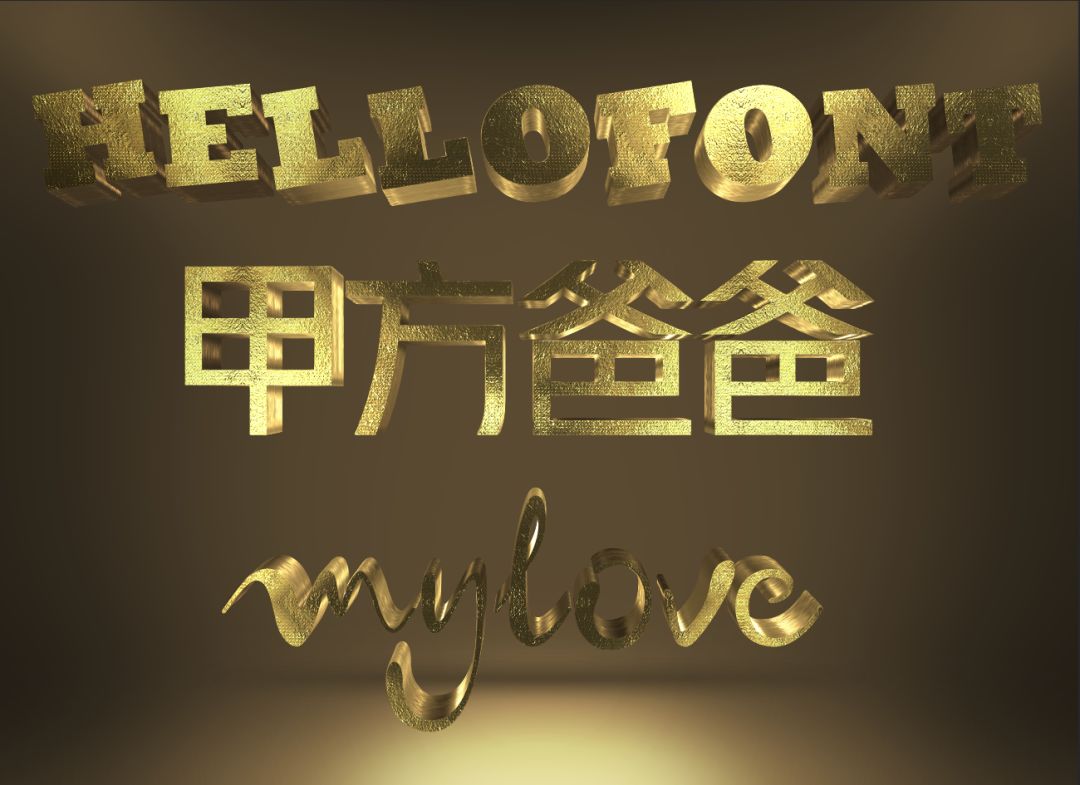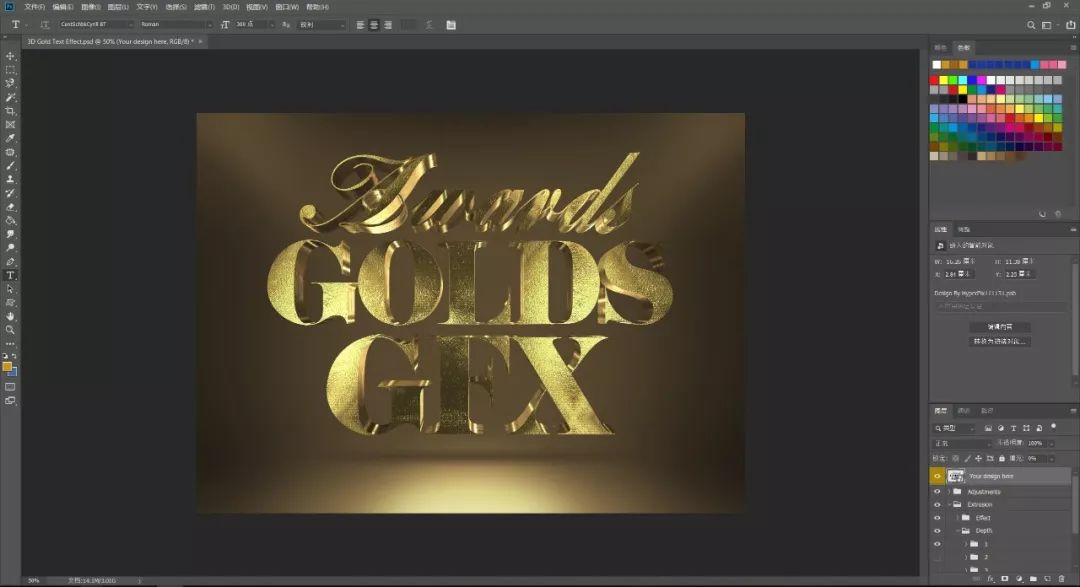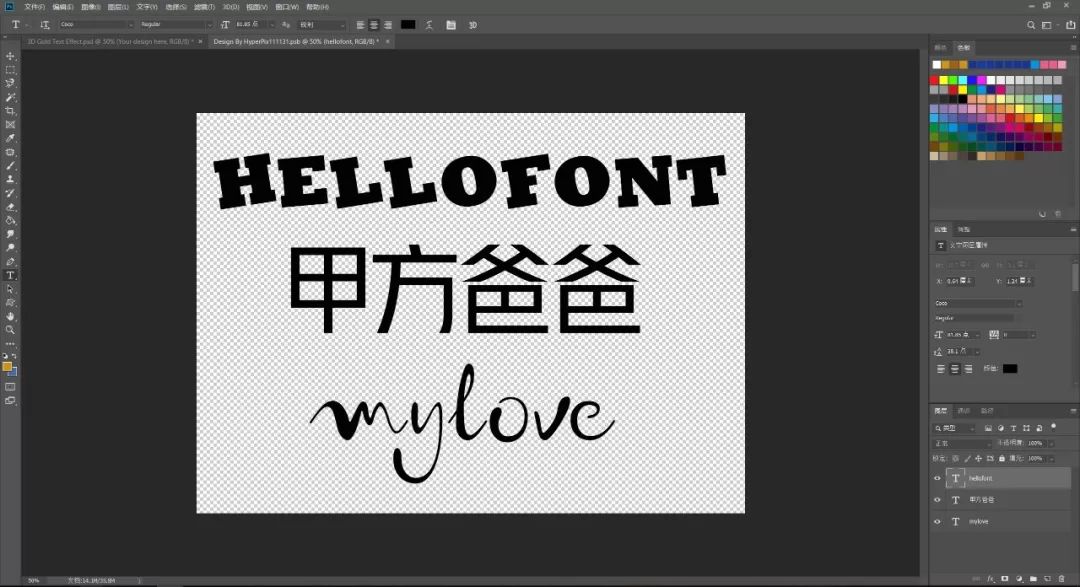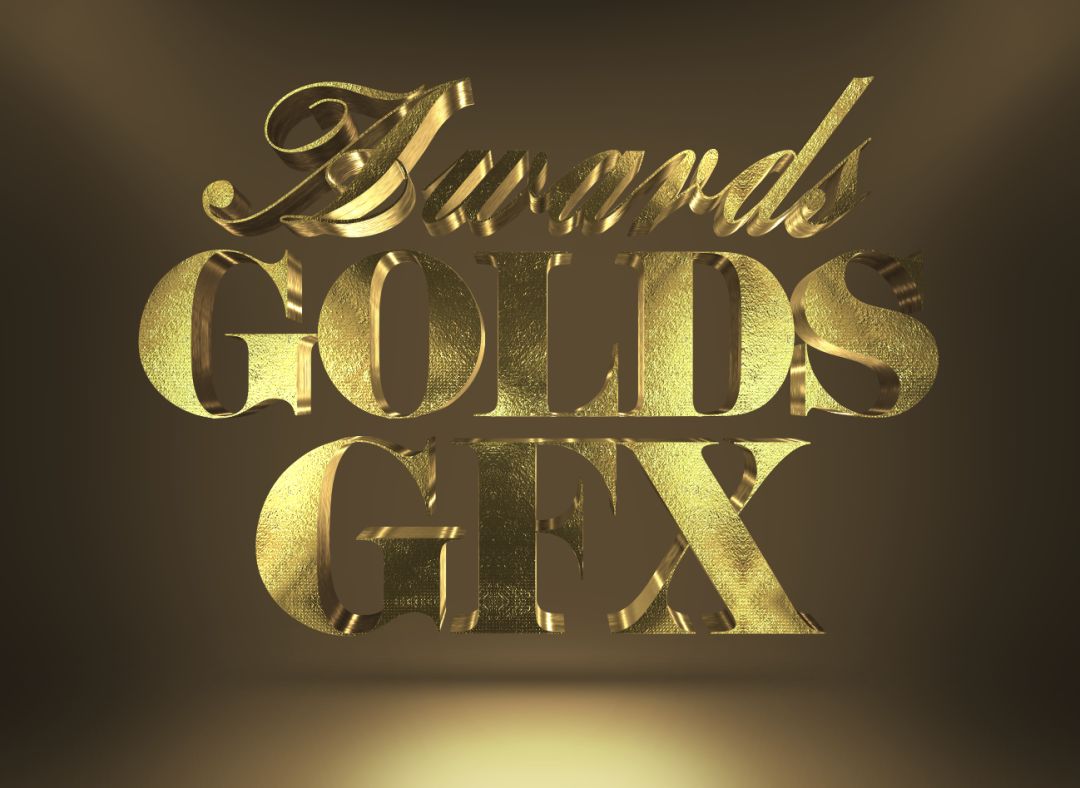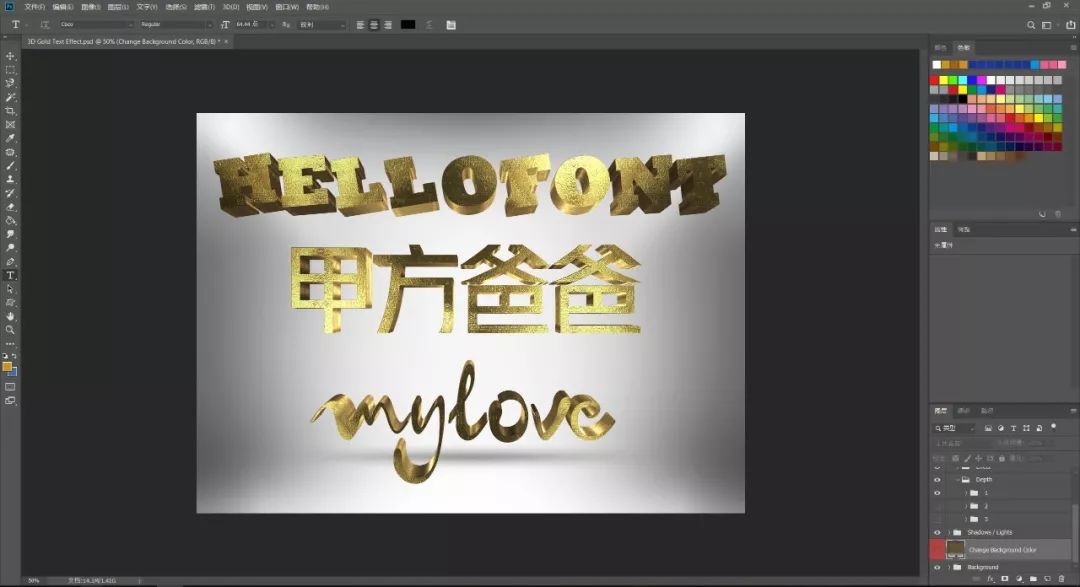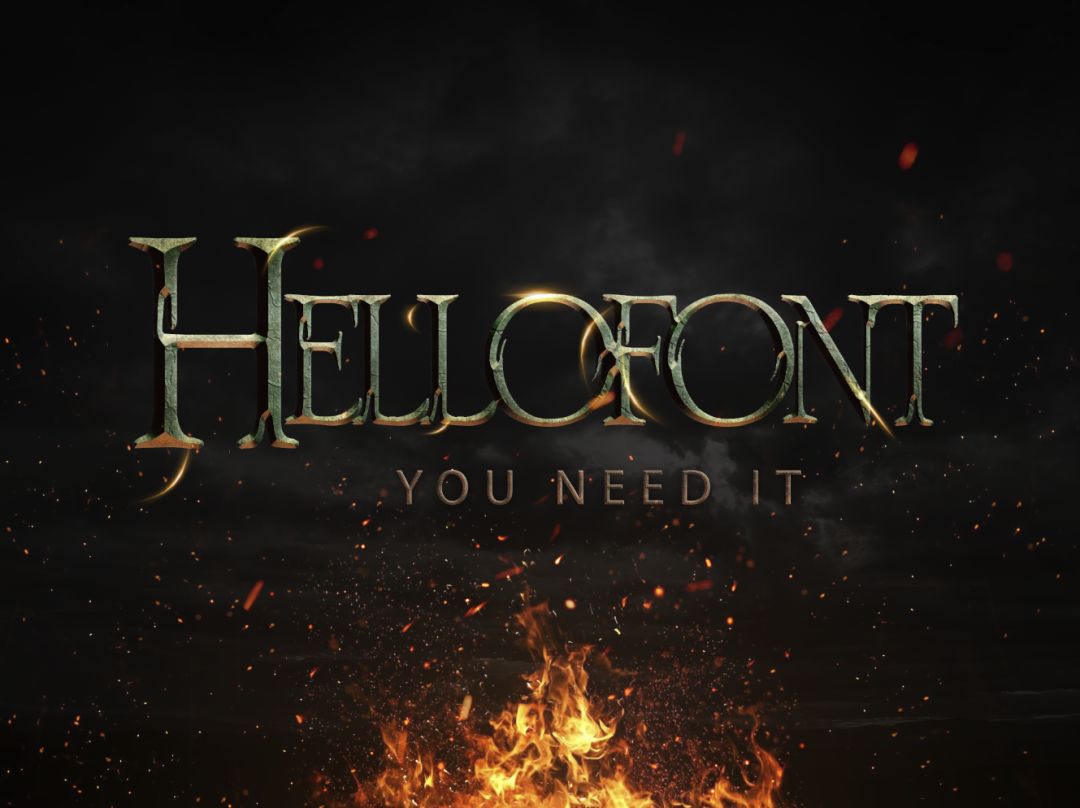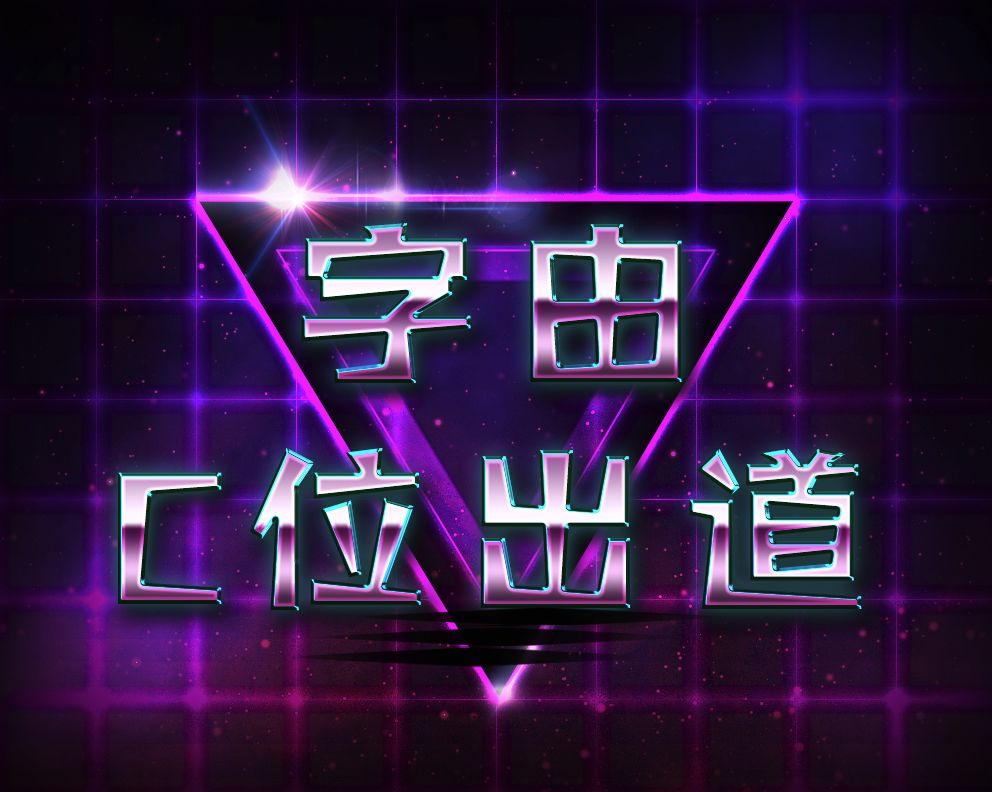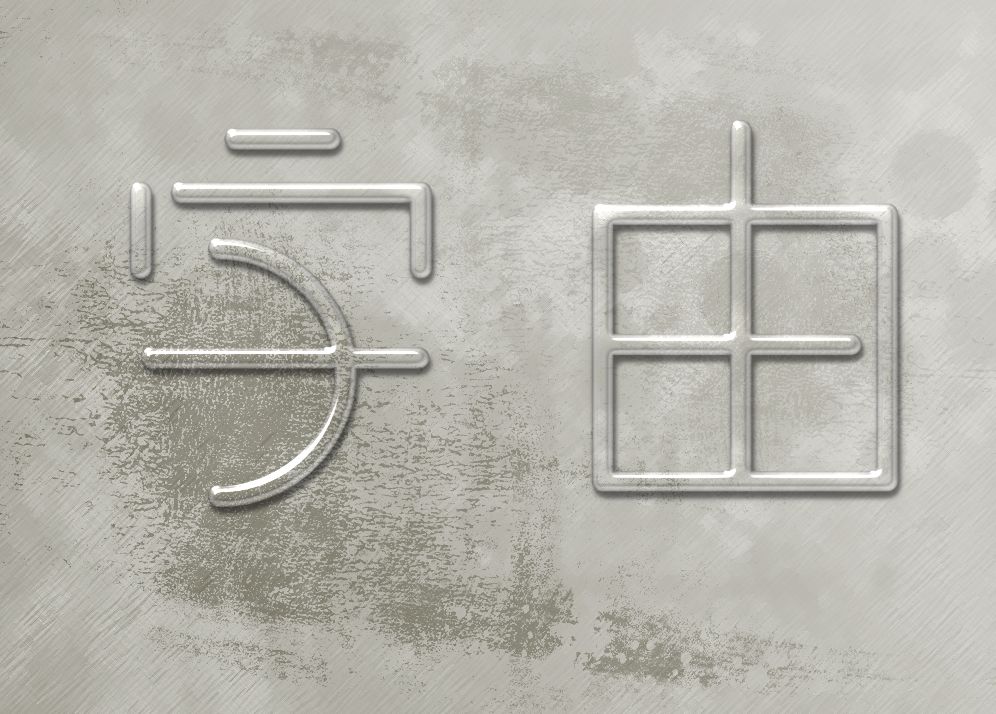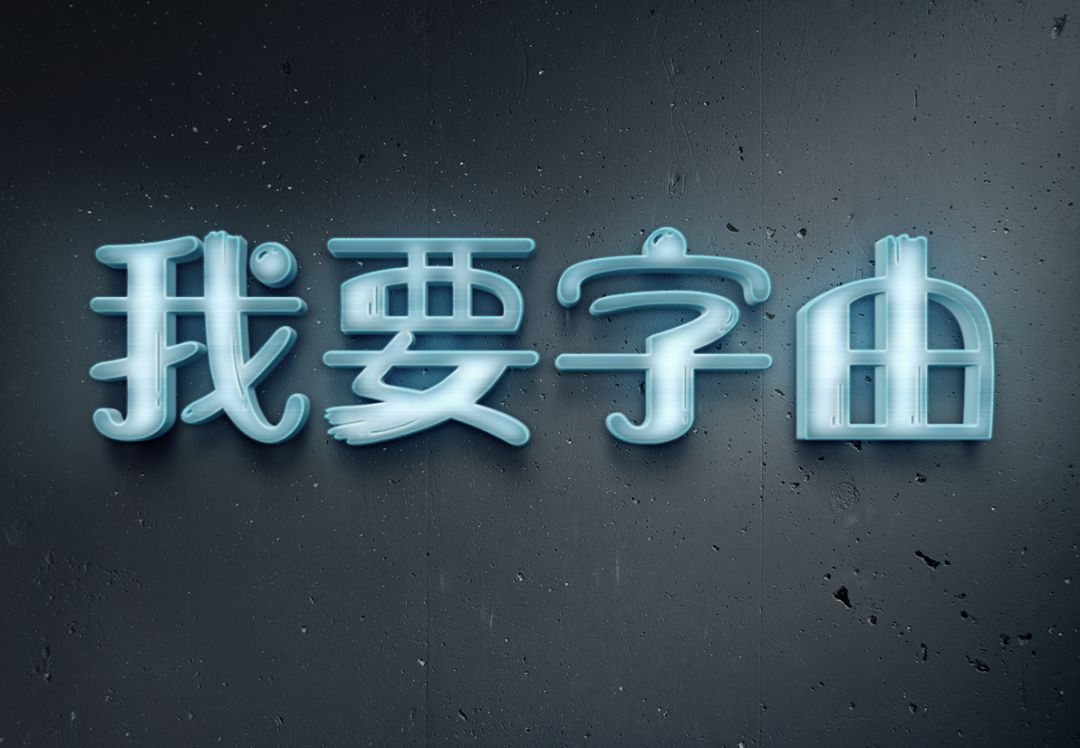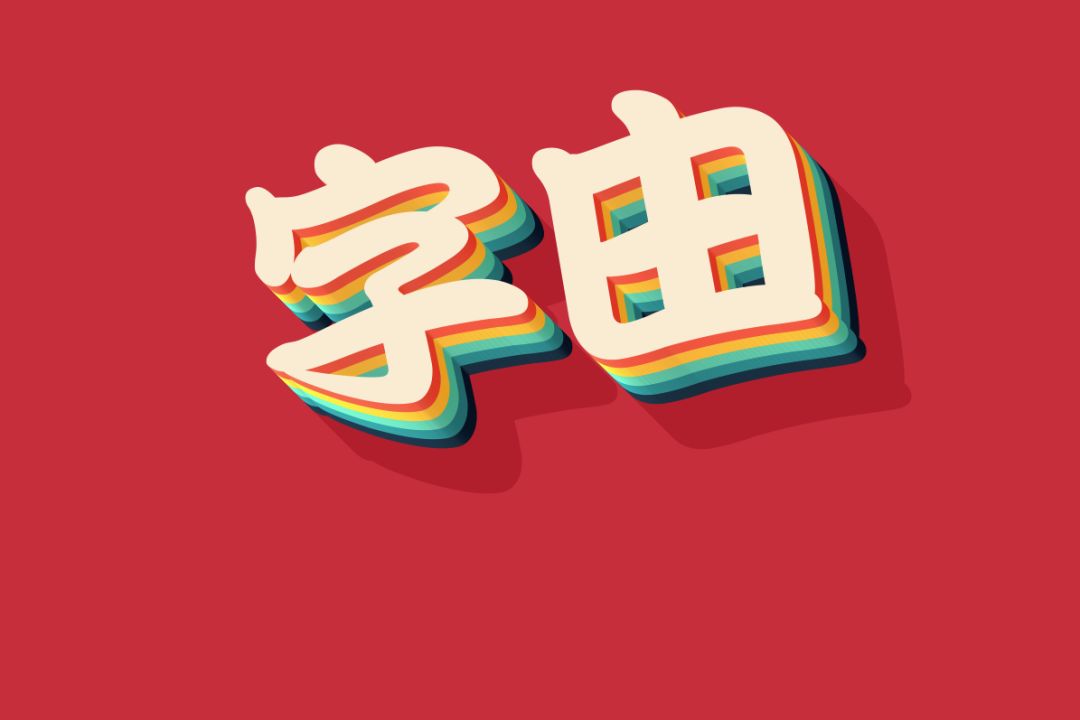
字由变换,特效也可以一键生成方法分享
今天柚子发现了一个新大陆,不光字体可以通过字由变换,特效也可以一键生成,再也不用眼睛看瞎了,到头来还是学不会那些霓虹灯、金属感的操作,严重被人怀疑智商……
所以我们继续偷懒,戳不想做图,只想一键偷懒,这3个“神操作”真是及时雨,不过今天的psd文件含金量很高,我考虑考虑给不给你们(傲娇脸)~
3D土豪金
甲方爸爸最喜欢,看着就贵气啊,可是要自己做,起码得一天吧,所以轮到我登场了~
双击黄色眼睛图层的缩略图。
然后改字体,英文的不够“土”,我们来个中文版~
打开字由,从上到下依次变换,Coco、汉仪雅酷黑、汉仪西文字体。
还没完,保存一下(ctrl+s)这个界面,再把它关闭,效果就出来了~
如果嫌背景颜色太深,也可以改,简直是傻瓜操作!
超燃金属感
这种效果是用得最多的,毕竟土豪金太赤裸裸,还是要低调的奢华,步骤和前面一样,我选了四款效果。
▲Crimes of Grindelwald
▲Eurostile LT Std
▲汉仪趣黑
▲变形金刚效果,也能字由变换
温柔女性
看了那么多直男效果,我们来点温柔如水的~
▲Lactosa
▲汉仪游园体
▲华康勘亭流
现代霓虹灯
▲汉仪星球体
▲Twilight New Moon
▲汉仪书魂体